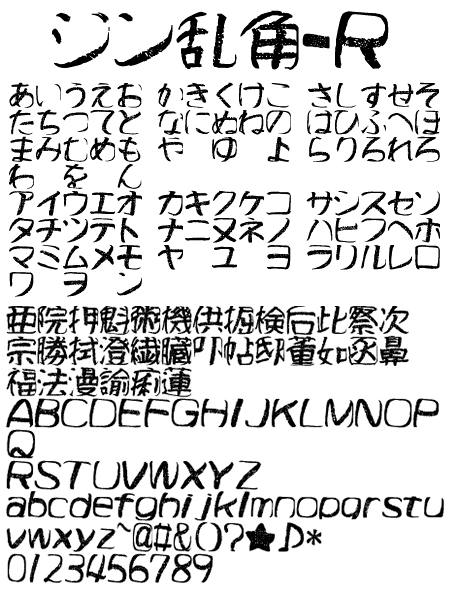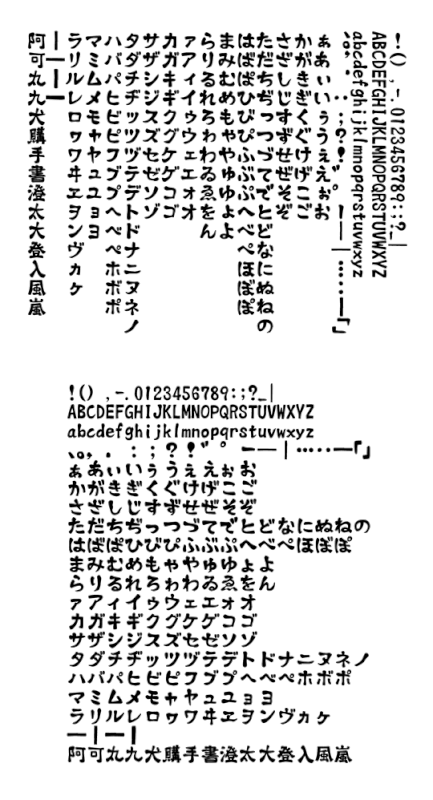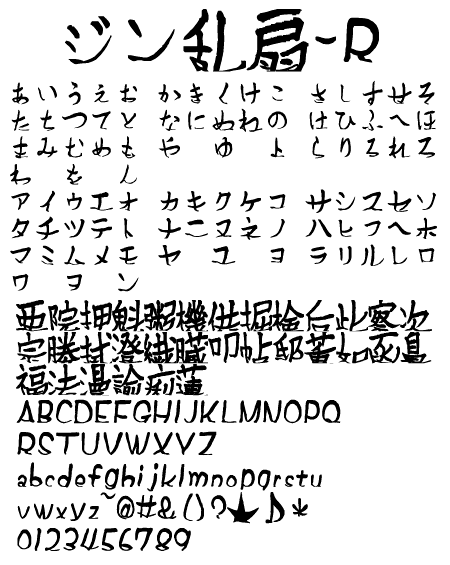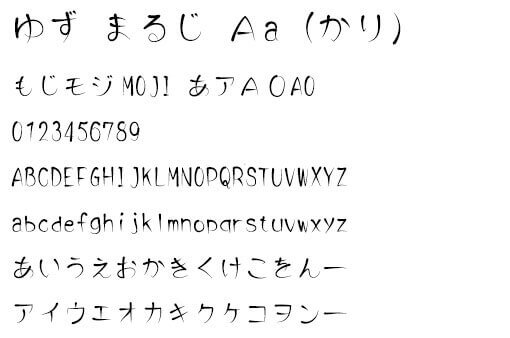
【厳選】無料でダウンロードできる毛筆フォント11個まとめ
無料でダウンロードできる毛筆フォントを集めてみました。テキストを入力するだけで手書き風の毛筆文字を表現することができます。
年賀状や暑中お見舞いなどにも使用できるフリーフォントになっています。和風のデザインには欠かせないフォントなのでこの機会に好みの毛筆フォントを試してみましょう!
g_太手書き丸
フェルトペン等のマーカーで描いた文字のようなフォント。コミックのセリフ、描き文字やロゴ等に利用可。
g_達筆(笑)
うまいっぽいけどうまいのかへたなのかよくわからない味のあるフォント。年賀状や、コミックの描き文字等にピッタリ。
GL-築地三号
活字体に近いかな文字。ひらがな・カタカナと記号が収録。
GL-築地四号
上記の「GL-築地三号」よりかっちりした形のかな文字。ひらがな・カタカナと記号が収録。
GL-築地五号
とても美しい書体。ひらがな・カタカナ記号と漢字若干数収録。
HOKKORIフォント
よく見ると、しっかりした明朝ではない、しかし、明朝より安心感を与えてくれるほっこりするフォント。
ジン乱角-R
クレヨンで書いたようなかすれた手書き風フォント。
ジン乱扇-R
毛筆で書いた文字を歪ませたような特徴的なフォント。
ゆず 丸字 A
インクが切れかかったマーカーで描いたようなフォント。
衡山毛筆フォント
書家の青柳衡山氏が揮毫及び作成したフォント。登録文字数は約13,000字。(Windows TrueTypeフォントの場合)
青柳衡山フォントT
書家の青柳衡山氏が揮毫及び作成したフォント。JIS非漢字、JIS第一水準漢字を収録。